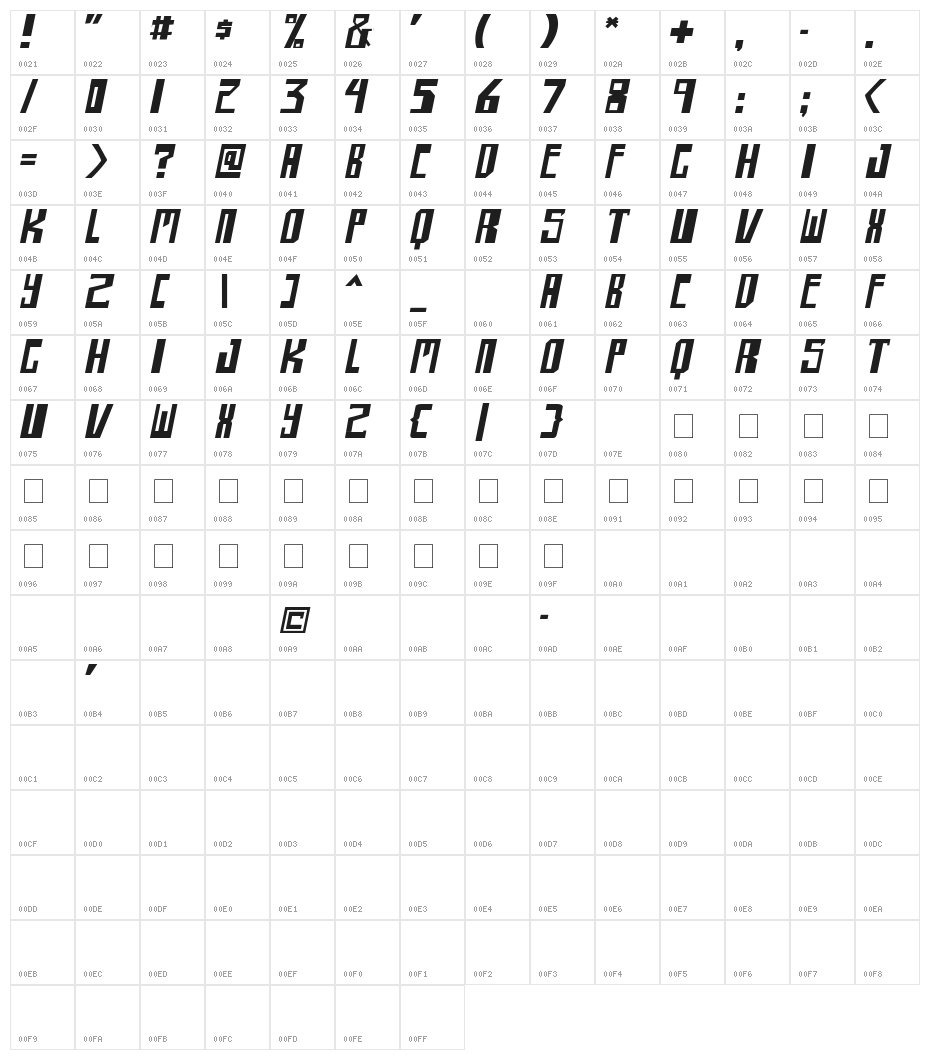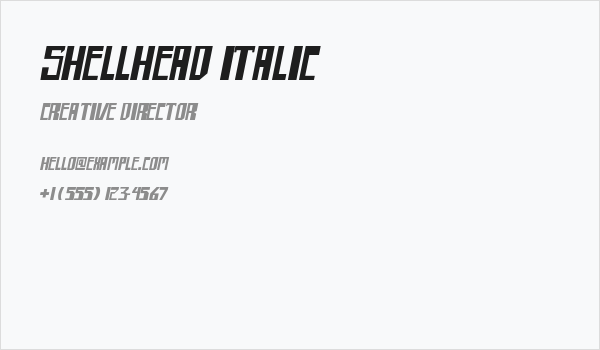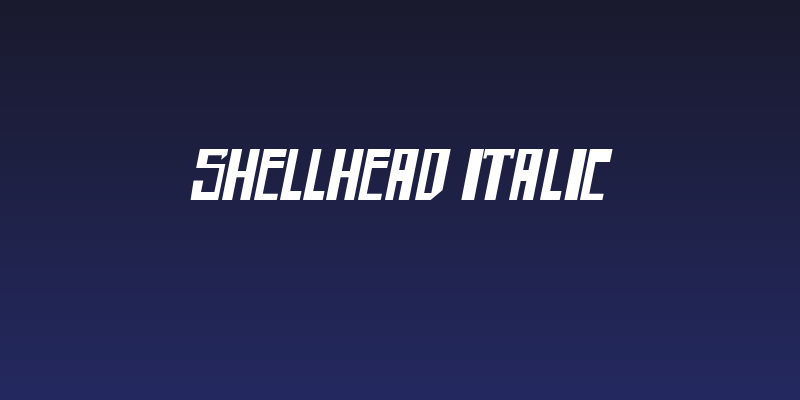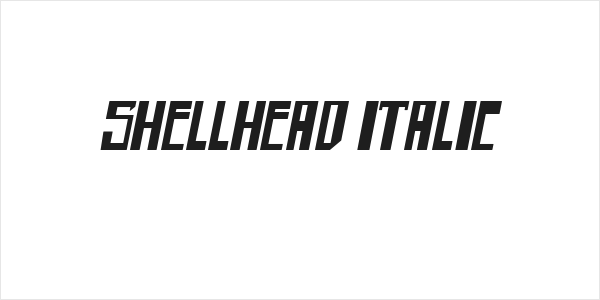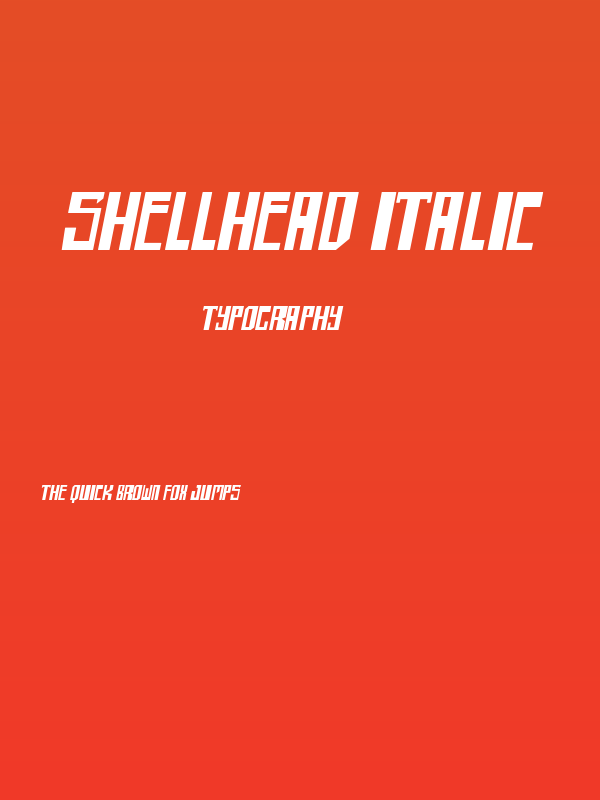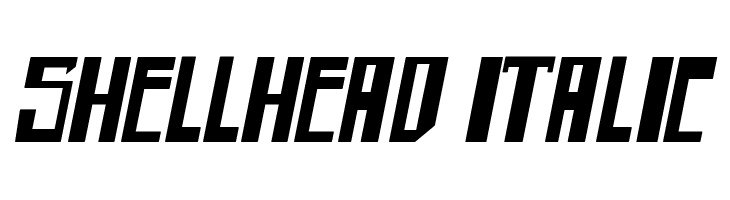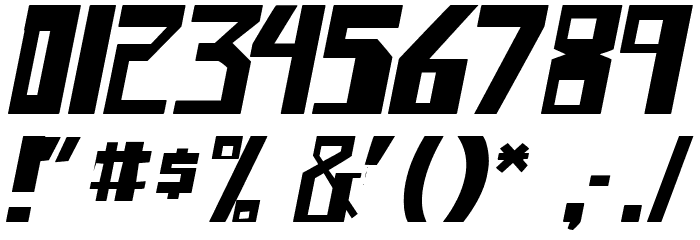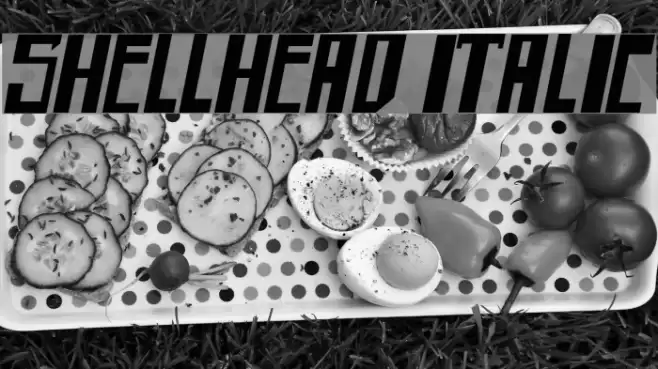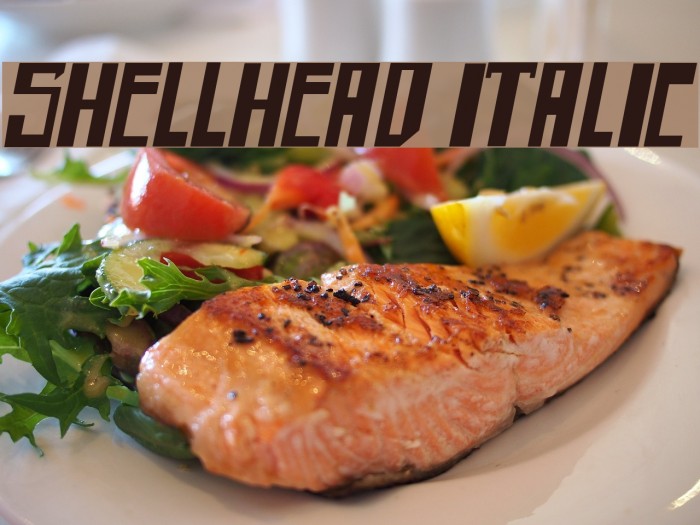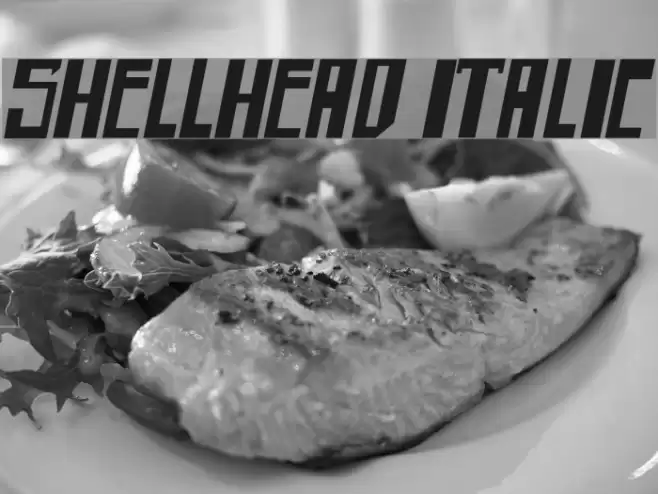
shellhead Italic Font
| Progetti proposti | Ideal for sci-fi themed designs, video game graphics, posters, and branding that requires a modern and edgy aesthetic. |